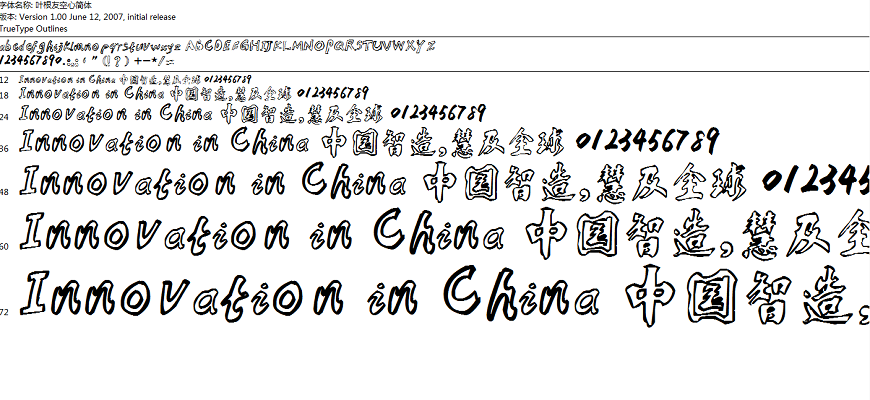
葉根友空心簡(jiǎn)體是一款特意為紀(jì)念香港回歸十周年所發(fā)布的書(shū)法字體,字體內(nèi)部全部鏤空,卻不會(huì)讓人覺(jué)得字體沒(méi)有骨干,反而給人一種別樣的立體感,非常的與眾不同,感興趣的朋友們快來(lái)下載吧!
葉根友空心簡(jiǎn)體是由中國(guó)書(shū)法奇人葉根友先生書(shū)寫,并在香港回歸十周年之際正式發(fā)布。 字體清晰自然,實(shí)用性強(qiáng),是書(shū)寫信件,BLOG等個(gè)性化字體的一不錯(cuò)的選擇.